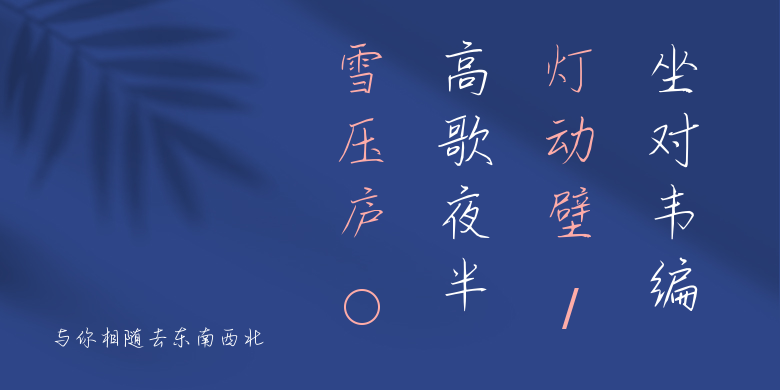
与你相随去东南西北
与你相随去东南西北,这款字体结构工整、笔画清晰,兼顾美观与易读性,适用于标题、正文、海报、包装、LOGO 等多种场景。字形优雅稳定,风格百搭耐看,适配日常排版与创意设计,让文字呈现更舒适、更具质感。与你相随去东南西北一笔一画,皆是细节,以均衡的比例、流畅的线条打造舒适视觉体验,字形端正大气,风格简约现代。无论是商业设计、品牌宣传还是日常排版,都能轻松驾驭,让文字更有格调与力量。与你相随去东南西北字体下载。